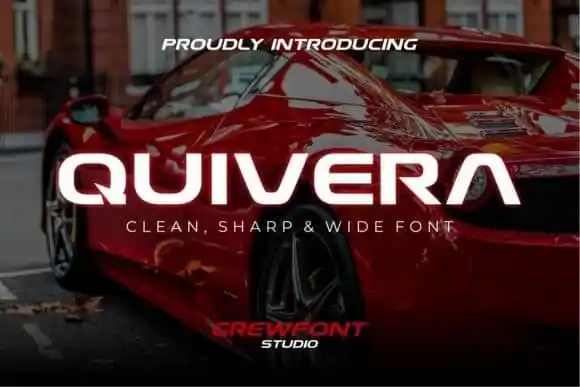
A Quivera Display Font é uma tipografia fresca, elegante e ousada para quem busca uma aparência vintage. Com traços marcantes e uma pegada peculiar, esta fonte é perfeita para criar um visual retro inovador. Ela foi criada pela Grewfont.studio e compartilhada na plataforma de design 99designs. Essencialmente projetada para headlines em todas as dimensões e para blocos de texto que apresentam tanto variação máxima quanto mínima, a Quivera se destaca como uma fonte ideal. Não importa o meio – seja web, impressão ou vídeos em movimento – essa fonte impressionante é certamente capaz de dar um visual estiloso e memorável. A sua simplicidade e diversidade fazem dela uma opção perfeita para designers que buscam novas maneiras de expressar ideias criativas.